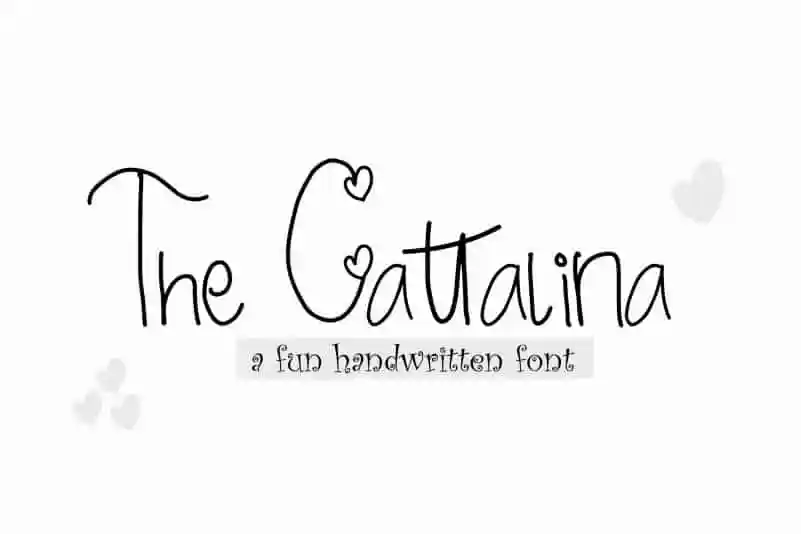
The Cattalina Handwritten Font – Fonte Grátis
The Cattalina Handwritten Font
A fonte ‘The Cattalina Handwritten Font’ é uma escolha perfeita para quem busca um estilo delicado e encantador para seus projetos digitais, seja para criar texturas criativas nas publicações de blog, adicionar um toque atraente aos títulos das matérias, promover produtos com elegância, ou decorar quadros de paredes com uma sensação única. Seja ela o centro do design de um item em uma embalagem ou o texto que complementa seu ambiente online, The Cattalina oferece uma infinidade de opções para personalizar suas criações. A fonte é perfeitamente adaptada a muitas finalidades, desde a escrita reflexiva até ao uso no design gráfico tradicional e digital. Sua simplicidade encantadora torna-a perfeita tanto para designers profissionais quanto para aqueles que desejam adicionar um toque pessoal aos seus projetos mais simples. Concebida pelo Linyeng_Studio, a The Cattalina Handwritten Font surge como uma opção irresistível para quem aprecia o charme de letras redondas e delicadas. O seu design elegante proporciona um acabamento sofisticado e encantador nas criações digitais. Não importa o propósito ou tamanho do projeto, a The Cattalina é uma fonte versátil que se adapta perfeitamente a todas as demandas, tornando-a uma excelente opção para aqueles buscando uma fonte de qualidade com um toque delicado e personalizado.
Designer: Linyeng_Studio